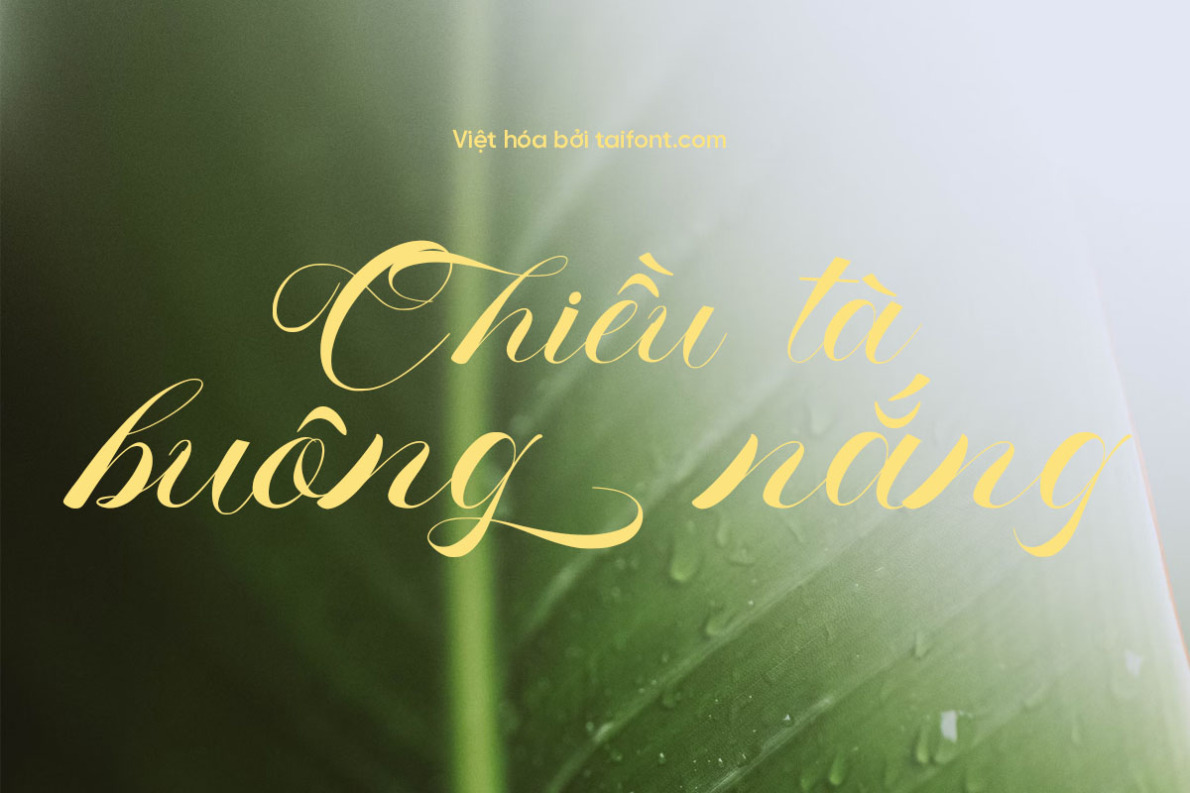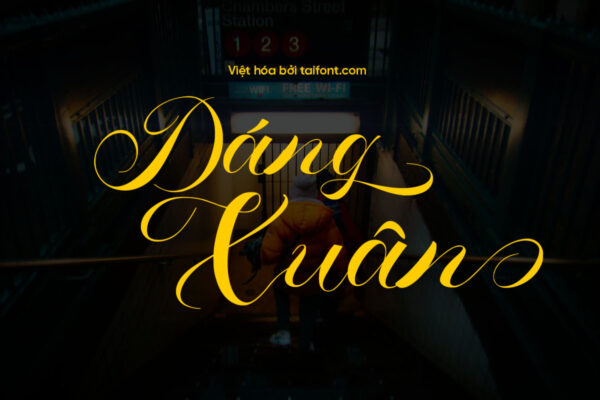
Giới thiệu Font TF Fopheras Việt hóa
TF Fopheras là một font viết tay thanh lịch với thiết kế các đường nét mềm mại, kèm theo bộ glyphs phong phú giúp các ký tự trở nên đa dạng và giàu cảm xúc. Với khả năng tạo ra những đường cong tinh tế và đầy nghệ thuật, font mang đến sự mềm mại và cao cấp cho bất kỳ thiết kế nào.
Phiên bản Việt hóa đã hỗ trợ đầy đủ dấu tiếng Việt, giữ nguyên phong cách viết tay duyên dáng và sang trọng. TF Fopheras đặc biệt phù hợp khi sử dụng cho các thiết kế thiệp cưới, thiệp mời sự kiện sang trọng, tiêu đề tạp chí thời trang, hoặc các ấn phẩm quảng bá mang tính cao cấp.
Nếu bạn đang tìm một font Việt hóa miễn phí mang hơi hướng viết tay tự nhiên, nghệ thuật và giàu ký tự thay thế, TF Fopheras chính là lựa chọn hoàn hảo.
Điểm nổi bật của TF Fopheras Việt hóa
Việt hóa đầy đủ dấu tiếng Việt.
Font viết tay sang trọng với bộ ký tự thay thế glyphs phong phú.
Lý tưởng cho thiệp cưới, thiệp mời sang trọng, tiêu đề tạp chí thời trang.
Tạo cảm giác thanh lịch, nghệ thuật và đẳng cấp.
Font TF Fopheras Việt Hóa – Font Viết Tay Sang Trọng Cho Thiệp Và Tiêu Đề Tạp Chí